今天分享来自日本著名设计师Masaomi Fujita的作品。
藤田雅臣的设计很是干净,这也许是日式设计的特有气质,耐看,细致,不负担。藤田的设计中带着轻松和惬意,还有几分可爱的趣味,设计风格展现了一种舒适的生活态度。若 MUJI 设计所呈现的生活态度是天然和简单,那么,藤田的设计便是将愉快的情绪带入了生活中。
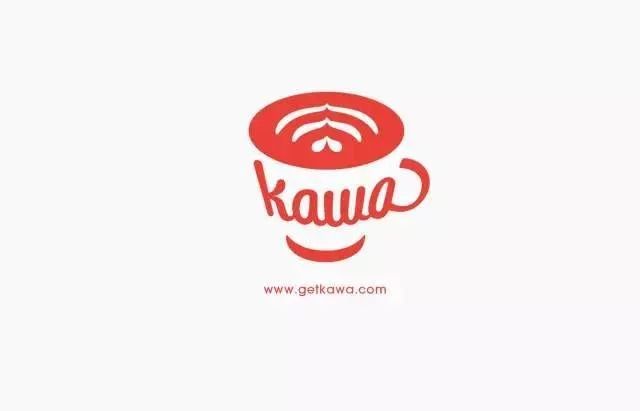
从Logo设计、字体设计、到平面作品等,将点睛的创意融入细节之处。他一定是个很爱生活的人吧。
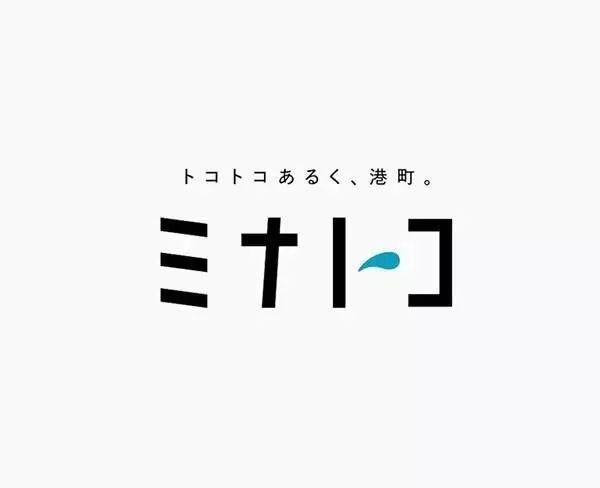
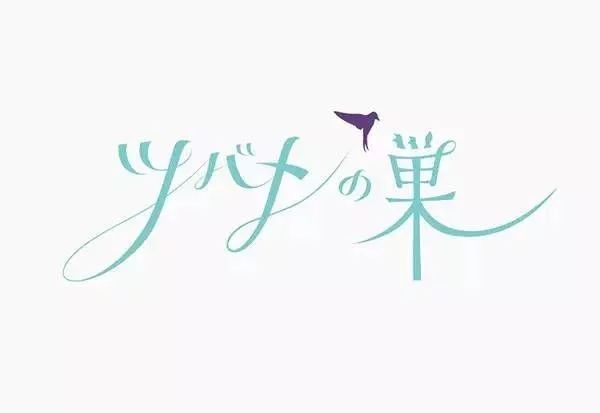
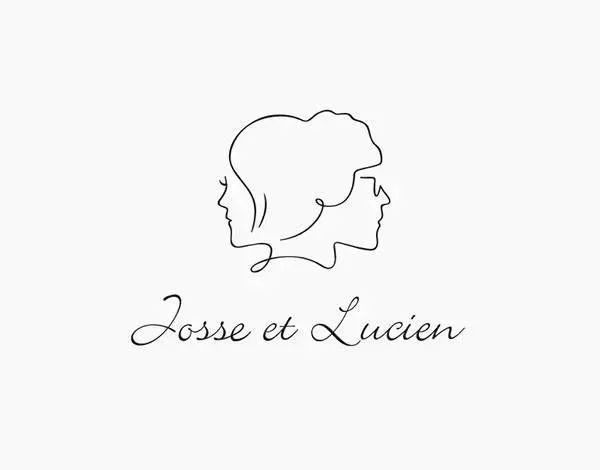
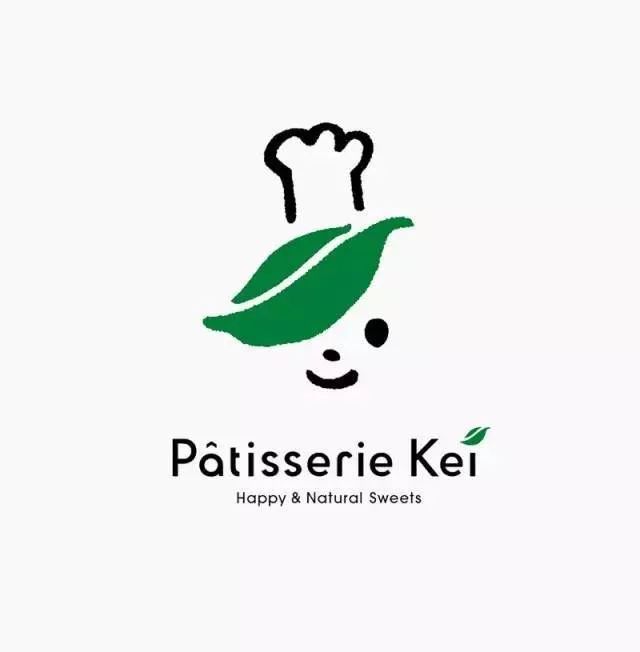
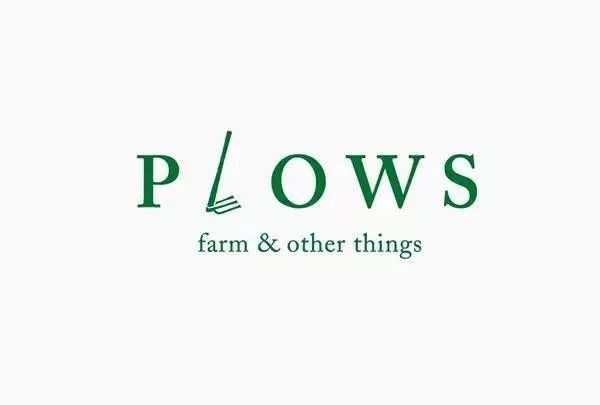
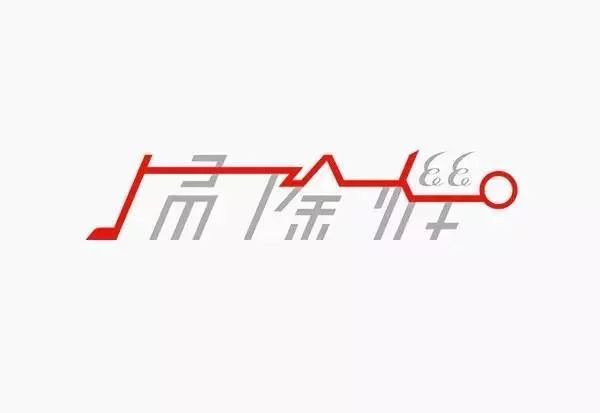
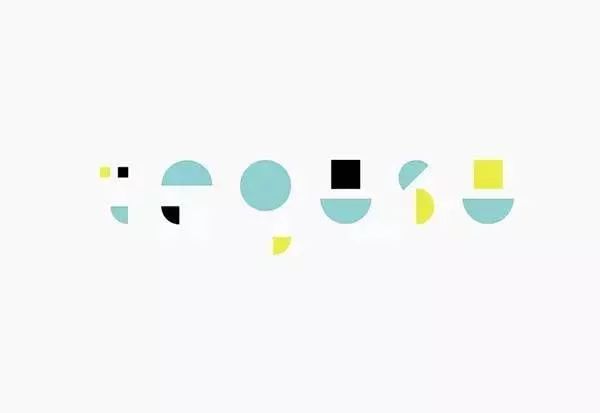
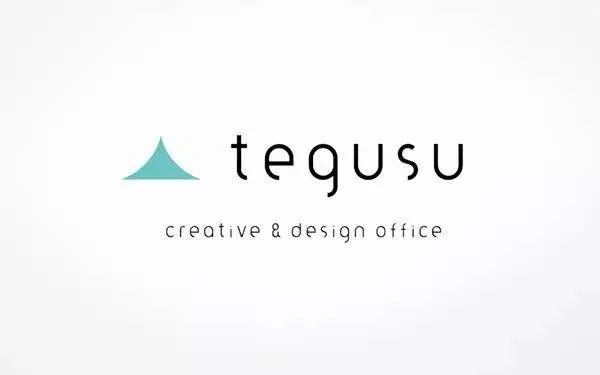
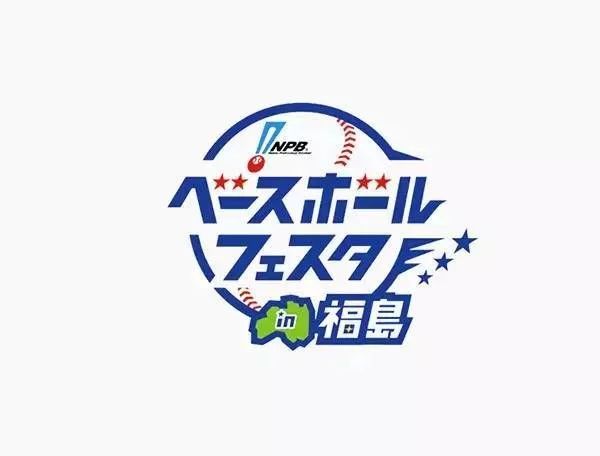
日本的设计一向很精美,
原标题:日本优秀的字体设计是怎么做出来的